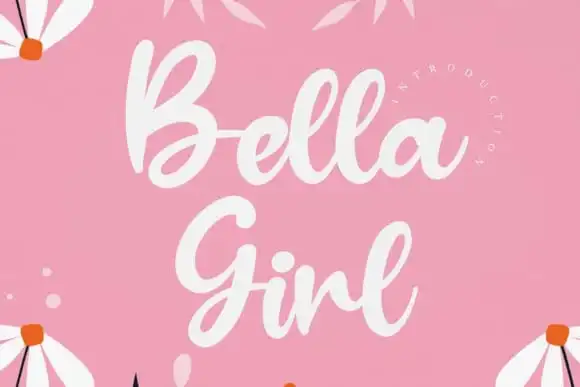
Bella Girl Script Font – Download Grátis
A Bella Girl Script Font é uma escolha elegante para qualquer projeto que você esteja planejando. Ela vem com letras minúsculas, maiúsculas e símbolos, garantindo total versatilidade. Além disso, contém muitas ligaturas, tornando o texto mais sofisticado e personalizado. Sua natureza é delicada e decorativa, com um acabamento que se assemelha a uma escrita ao vivo, oferecendo um toque de charme especial para qualquer design. Ideal tanto para branding e embalagens de produtos quanto para cartões de convite, citações, camisetas, rótulos, anúncios e logos, ela é perfeita para ilustrar suas ideias criativas em uma linguagem atraente e moderna. Descubra por si mesmo o encanto da Bella Girl Script Font. Ela não apenas personaliza seu design visual, mas também ajuda a construir um vínculo emocional com seu público-alvo. Através de textos agradáveis e elegantes, ela pode transformar qualquer projeto em uma peça única e memorável.